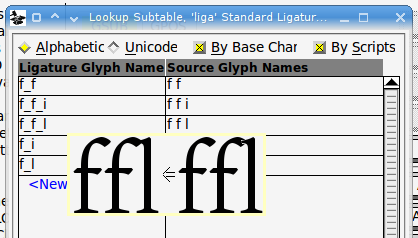
Grossartig, noch mehr Gentium, und noch mehr Font-Intelligenz! Mir ist allerdings nicht ganz klar, warum diese Neuheiten nicht in den normalen Gentium-Font integriert werden, oder ob so eine Integration dereinst geplant ist. Was nützt eine Multiplizierung der Gentium-Fonts?
Ich denke schon, daß die „Plus“-Variante dann zum Schluß wohl als einzige übrigbleiben wird. Im Moment ist es ja eben nur eine Testversion.
Seh ich das richtig, dass Ligaturen derzeit nur in der Kursiven enthalten sind?
Also laut Fontlab-Datei sind fi, fl, ff, ffi, ffl in beiden Fonts enthalten, regular und italic.
Allerdings haben sie laut vfb-Quell-Datei kein LIGA-Feature eingebaut. Wenn die Ligaturen also auftauchen, dann macht das Satzprogramm das selbstständig.
Es gibt Glyphen für die gängigen f-Ligaturen und sie werden auch standardmäßig aktiviert (»liga«). Die Glyphen sehen nur nicht aus wie typische f-Ligaturen (die waagerechten Striche sind bei ff nicht verbunden; der i-Punkt bei fi ist noch da …).
Naja, in den Gentium-FAQ heißt es dazu:
In Gentium-Regular there is really no need for a ligature, and because of the design of the f and i, a ligature would tend to look out of place. But if you look in Gentium-Italic, you'll see 'fi' and 'ffi' ligatures. They still have a separate dot on the 'i', but are connected.
Sicher, aber trotzdem sind Ligaturen vorhanden und standardmäßig aktiviert. Sie sind nur visuell identisch zu den Einzelbuchstaben. Warum? Keine Ahnung. Gibt’s da irgendwelche technischen Gründe? Mir fallen eher Nachteile ein, z.B. wenn Text gesperrt werden soll. Den z.B. beim Fraktur-ck beabsichtigten Effekt will man bei den f-Ligaturen ja gerade nicht haben.
Da die Ligaturen im OpenType-Feature "liga" definiert sind, sollte eigentlich kein nachteiliger Effekt beim Sperren auftreten – solche Ligaturen sollten beim Sperren nicht gesetzt werden. Allerdings geschieht dies trotzdem in einigen Programmen, etwa in TextEdit.app oder Firefox auf Linux oder Windows (Firefox auf Mac OS X hingegen oder InDesign tun es korrekt). Die obligatorischen Fraktur-Ligaturen ch, ck, ?t und tz werden im Unterschied dazu im OpenType-Feature "rlig" definiert, so dass sie beim Sperren erhalten bleiben.
Was das Sperren angeht, ist also an dieser Codierung in Gentium Plus eigentlich nichts auszusetzen (wozu man allerdings Gentium Plus sperren sollte, wäre eine andere Frage).
Warum? Keine Ahnung. Gibt’s da irgendwelche technischen Gründe? Mir fallen eher Nachteile ein, z.B. wenn Text gesperrt werden soll. Den z.B. beim Fraktur-ck beabsichtigten Effekt will man bei den f-Ligaturen ja gerade nicht haben.
Die Standard-f-Ligaturen sind teil des Basiszeichensatzes einer Schrift. Manche (alte, opentype-dumme) ligaturfähige Programme erwarten diese Zeichen an ihrem gewohnten Platz, und zeigen Platzhalter oder gar nichts, wenn sie eine Ligatur generieren, diese aber im Font nicht vorhanden ist, selbst wenn die Einzelzeichen da wären.
Ergo: die Ligaturen müssen technisch vorhanden sein - ob sie dann optisch anders sind als die Einzelzeicheen, ist eben eine Gestaltungsfrage.
Die Standard-f-Ligaturen sind teil des Basiszeichensatzes einer Schrift. Manche (alte, opentype-dumme) ligaturfähige Programme erwarten diese Zeichen an ihrem gewohnten Platz
Was bedeutet »an ihrem gewohnten Platz«? Dass f-Ligaturen manchmal über ihre Unicode-Werte eingefügt werden (und das deshalb z.B. auf Position U+FB00 – dem Wert für »ff« – was stehen sollte), kann ich noch nachvollziehen. Aber gibt es auch (nicht-OT-fähige) Software, die das über die Glyphnamen macht? Gentium Plus hat z.B. gleich zwei ff-Ligaturen: einmal auf U+FB00 den Glyphen »ff« und dann nochmal ohne Unicode-Wert den Glyphen »f_f«. Beide sehen identisch zu den Einzelbuchstaben »ff« aus. Aber OK, wenn bestimmte Software nach diesen Glyphennamen sucht, soll man das halt auch einbauen. Bloß was ich absolut nicht verstehe ist, warum dann auch noch eine liga-Tabelle angelegt werden muss. Gibt’s dafür irgendeinen technischen Grund?
Die Standard-f-Ligaturen sind teil des Basiszeichensatzes einer Schrift. Manche (alte, opentype-dumme) ligaturfähige Programme erwarten diese Zeichen an ihrem gewohnten Platz
Was bedeutet »an ihrem gewohnten Platz«? Dass f-Ligaturen manchmal über ihre Unicode-Werte eingefügt werden (und das deshalb z.B. auf Position U+FB00 – dem Wert für »ff« – was stehen sollte), kann ich noch nachvollziehen. Aber gibt es auch (nicht-OT-fähige) Software, die das über die Glyphnamen macht? Gentium Plus hat z.B. gleich zwei ff-Ligaturen: einmal auf U+FB00 den Glyphen »ff« und dann nochmal ohne Unicode-Wert den Glyphen »f_f«. Beide sehen identisch zu den Einzelbuchstaben »ff« aus. Aber OK, wenn bestimmte Software nach diesen Glyphennamen sucht, soll man das halt auch einbauen. Bloß was ich absolut nicht verstehe ist, warum dann auch noch eine liga-Tabelle angelegt werden muss. Gibt’s dafür irgendeinen technischen Grund?[/quote:1beo2f2l]
Die "neue", anerkannte Methode, Ligaturen abzulegen, ist die Benamung mit _ (f_f) und *kein* Unicode-Wert. Grundsätzlich sollte man alle Mitglieder einer Zeichengruppe gleich behandeln, d.h. alle Ligaturen nach diesem Schema ablegen, nicht die einen so, und die anderen ("alten") noch auf die alte Methode, also mit eigenem Codewert.
Da man aber gleichzeitig kompatibel sein will/muss (man weiß ja nie wo und wie die Schrift eingesetzt wird), sollte man der Glyphe auch nach ihrem bisherigen Namen benennen und einen Codewert geben ...
(Dass man die historisch entstandenen Unicodepositionen von ff, fi etc. nicht einfach leer lassen sollte, wenn man um 100%ige Kompatibilität bemüht ist, steht ja auf einem anderen Blatt.)
Widerspruch?